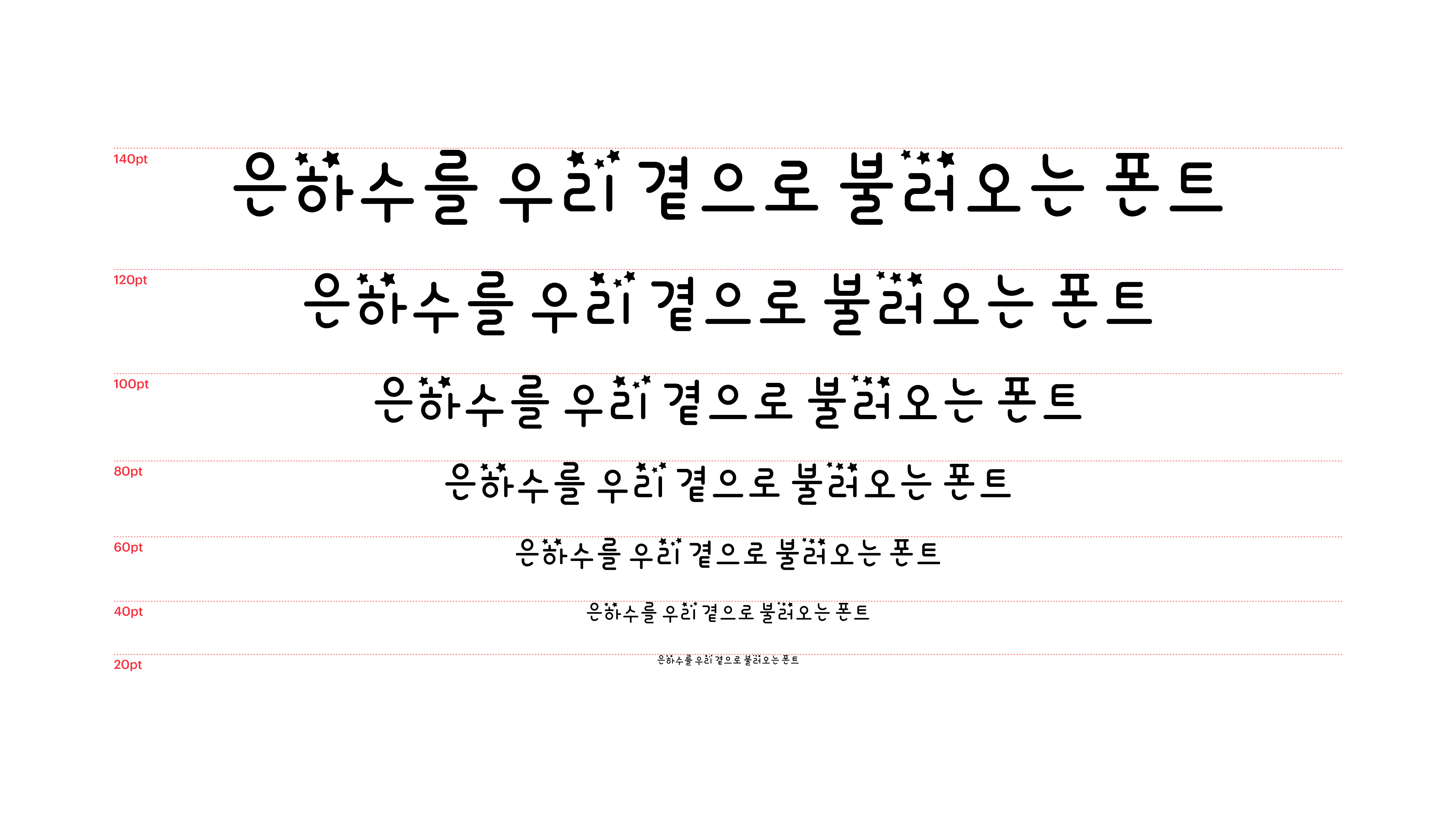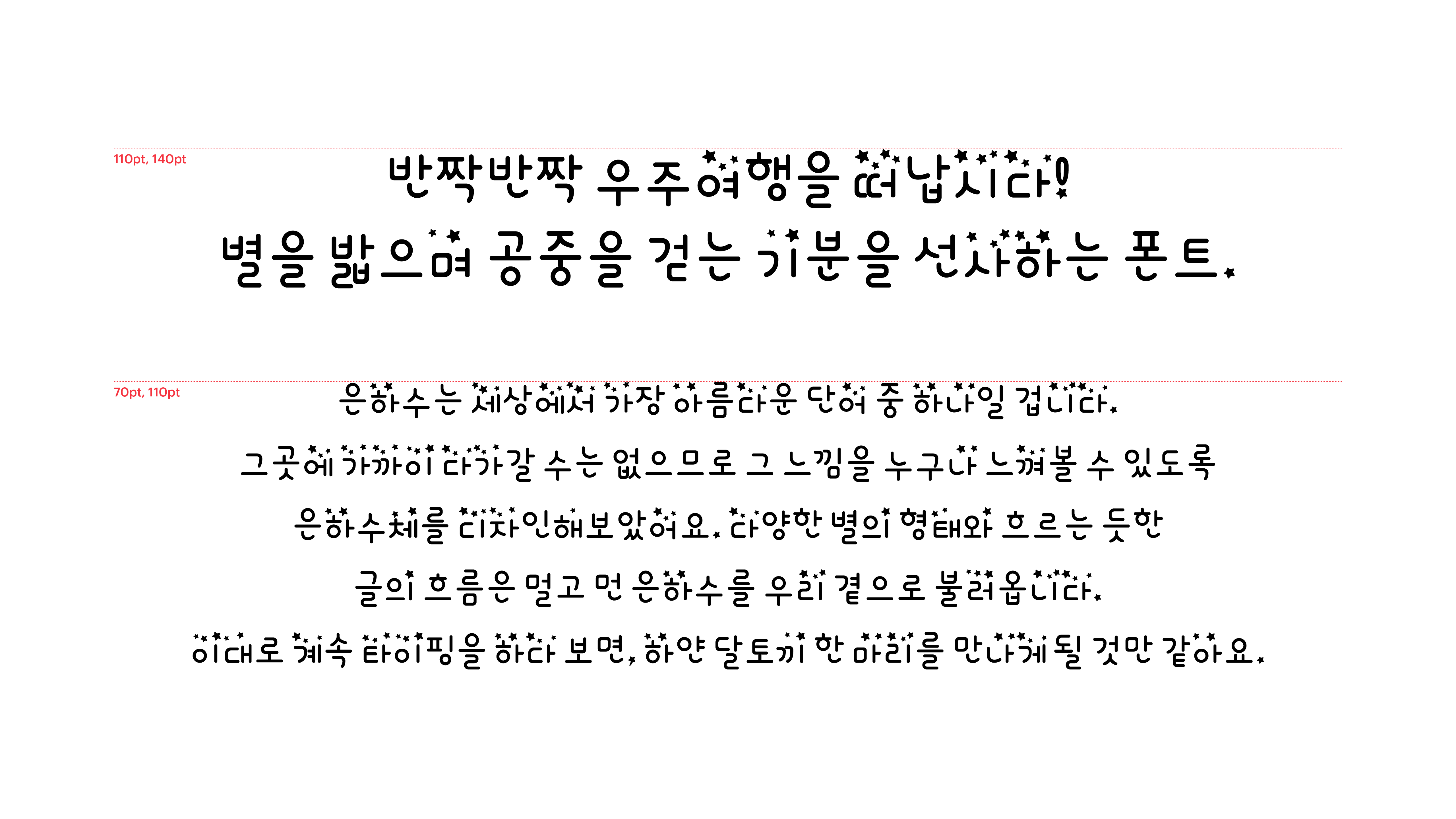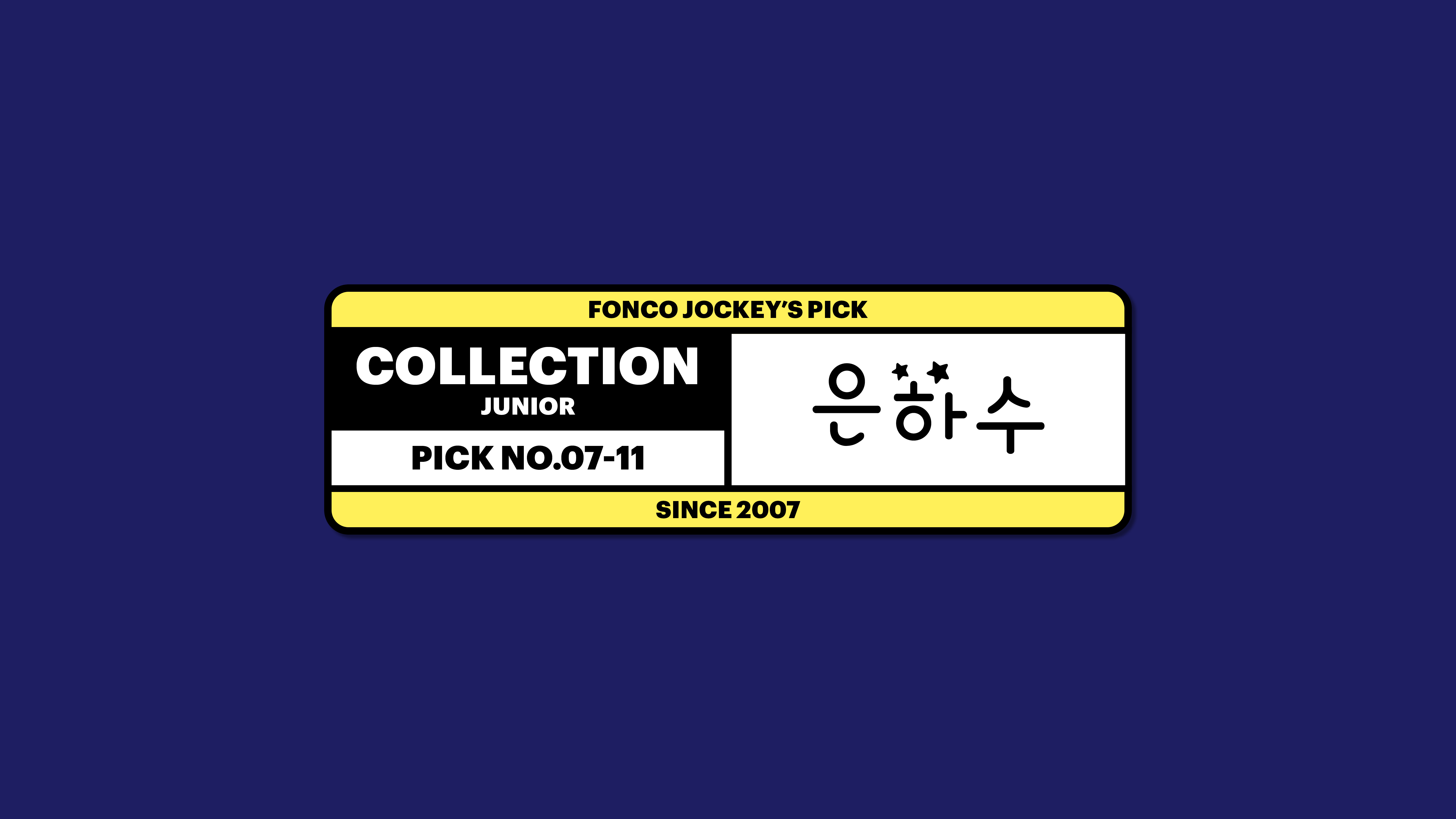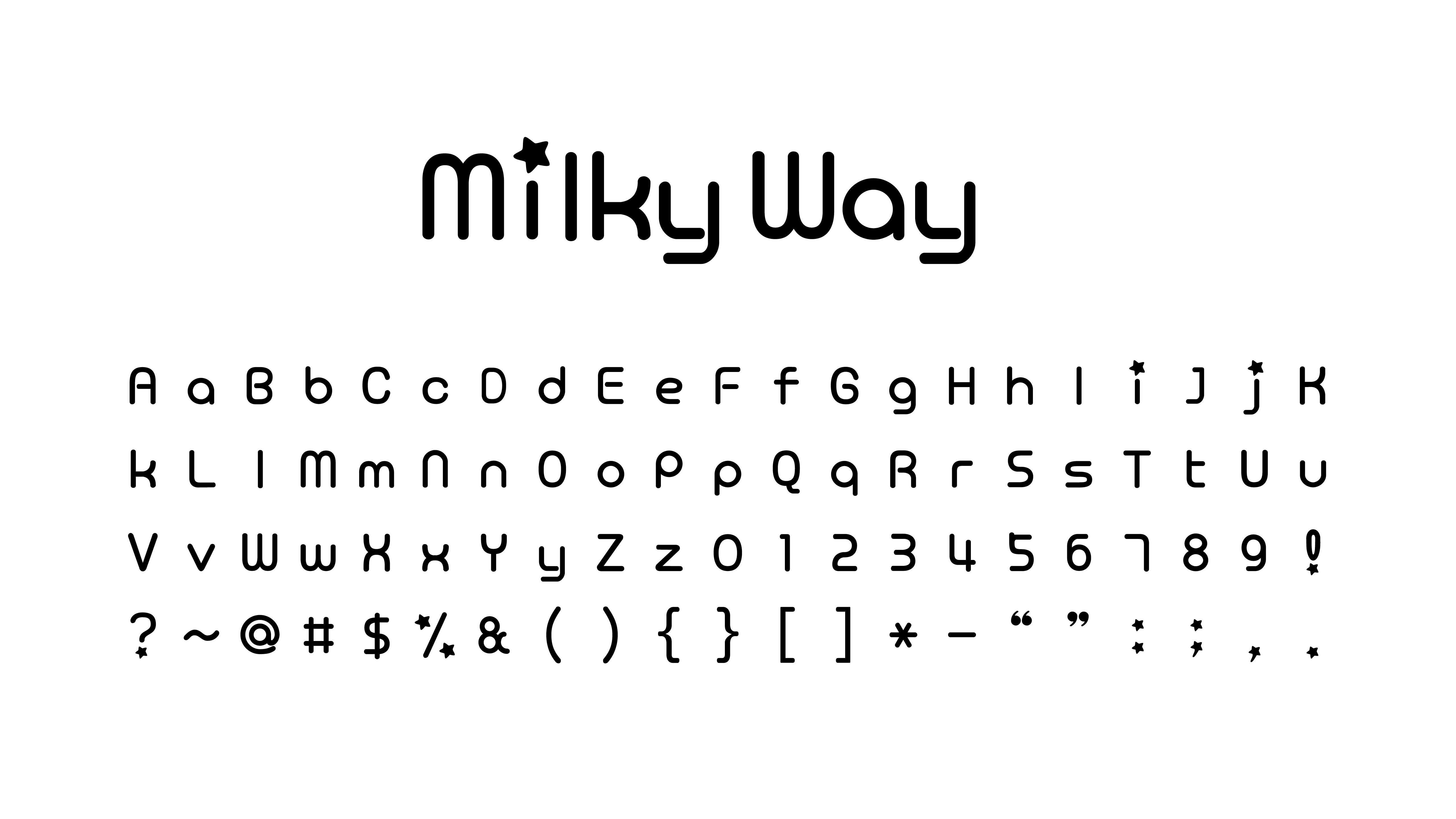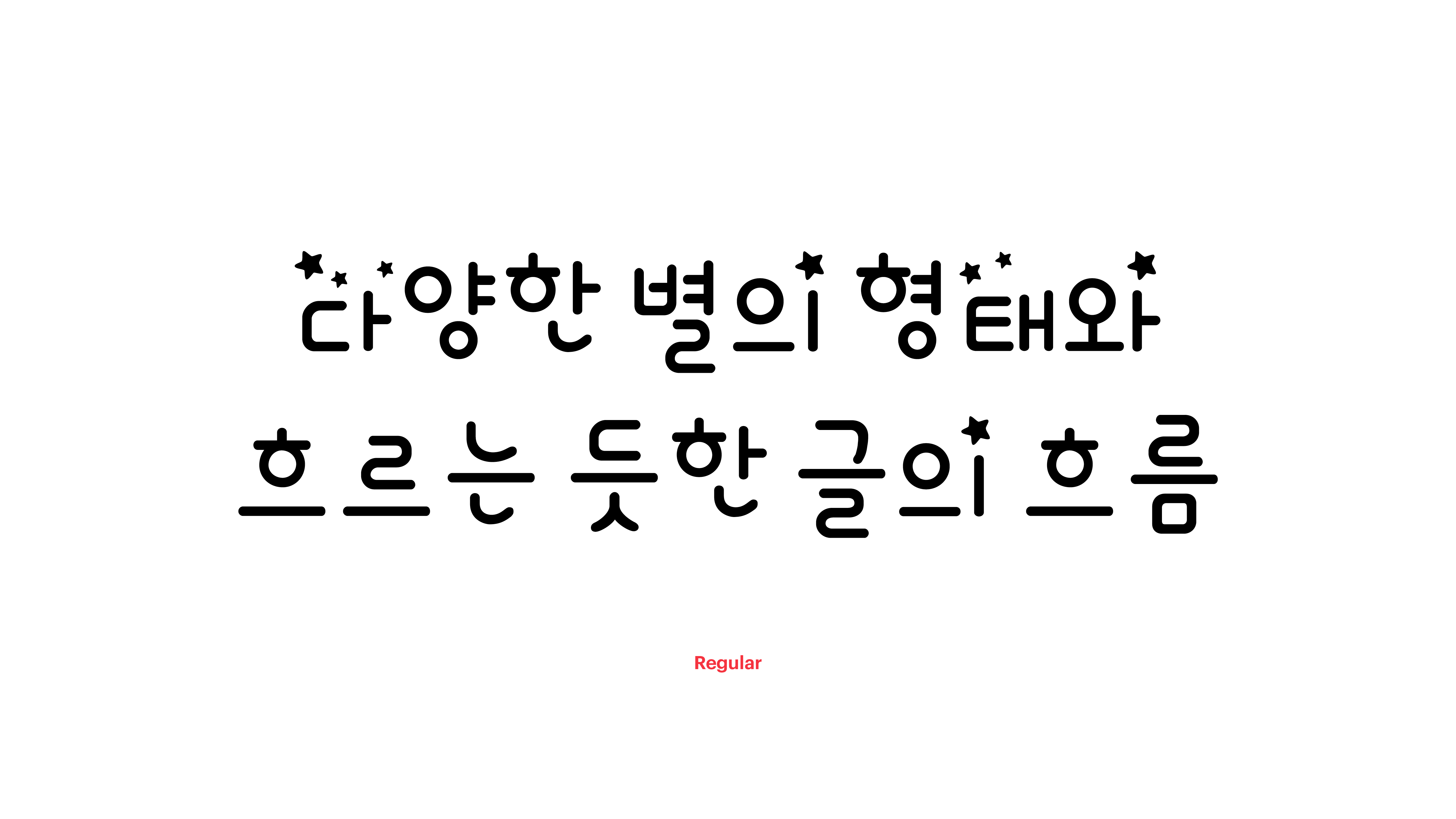
은하수
Yoon 은하수
은하수는 세상에서 가장 아름다운 단어 중 하나일 겁니다. 그곳에 가까이 다가갈 수는 없으므로 그 느낌을 누구나 느껴볼 수 있도록 은하수체를 디자인해보았어요. 다양한 별의 형태와 흐르는 듯한 글의 흐름은 멀고 먼 은하수를 우리 곁으로 불러옵니다. 이대로 계속 타이핑을 하다보면, 하얀 달토끼 한 마리를 만나게 될 것만 같아요.